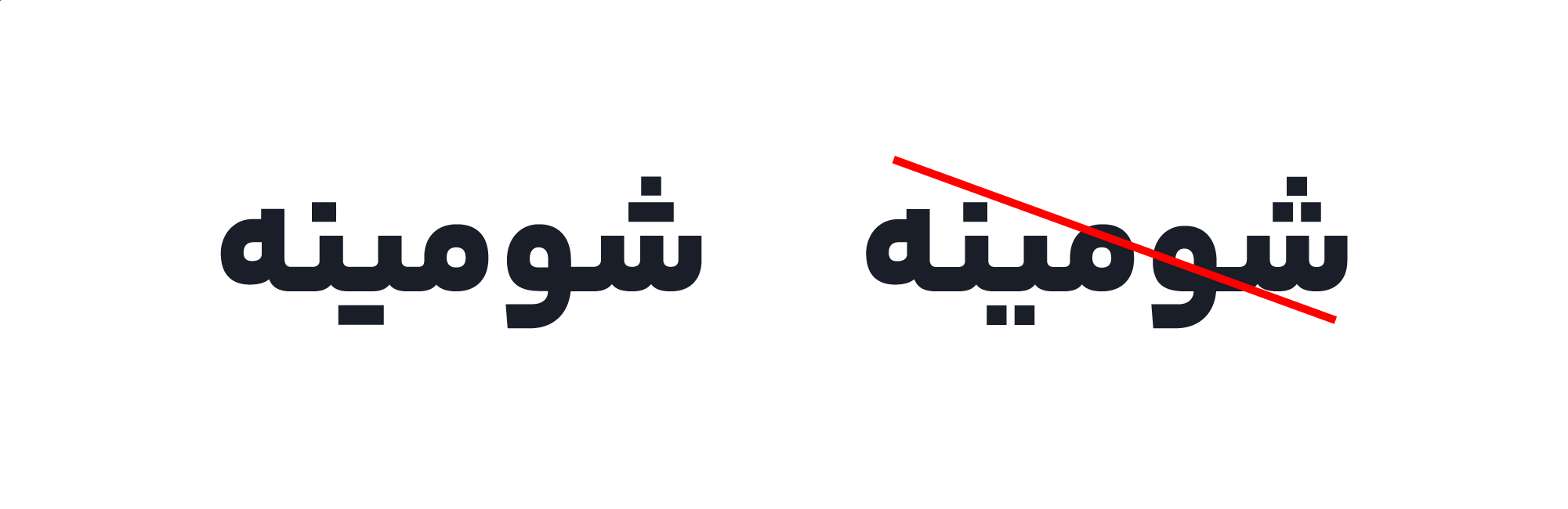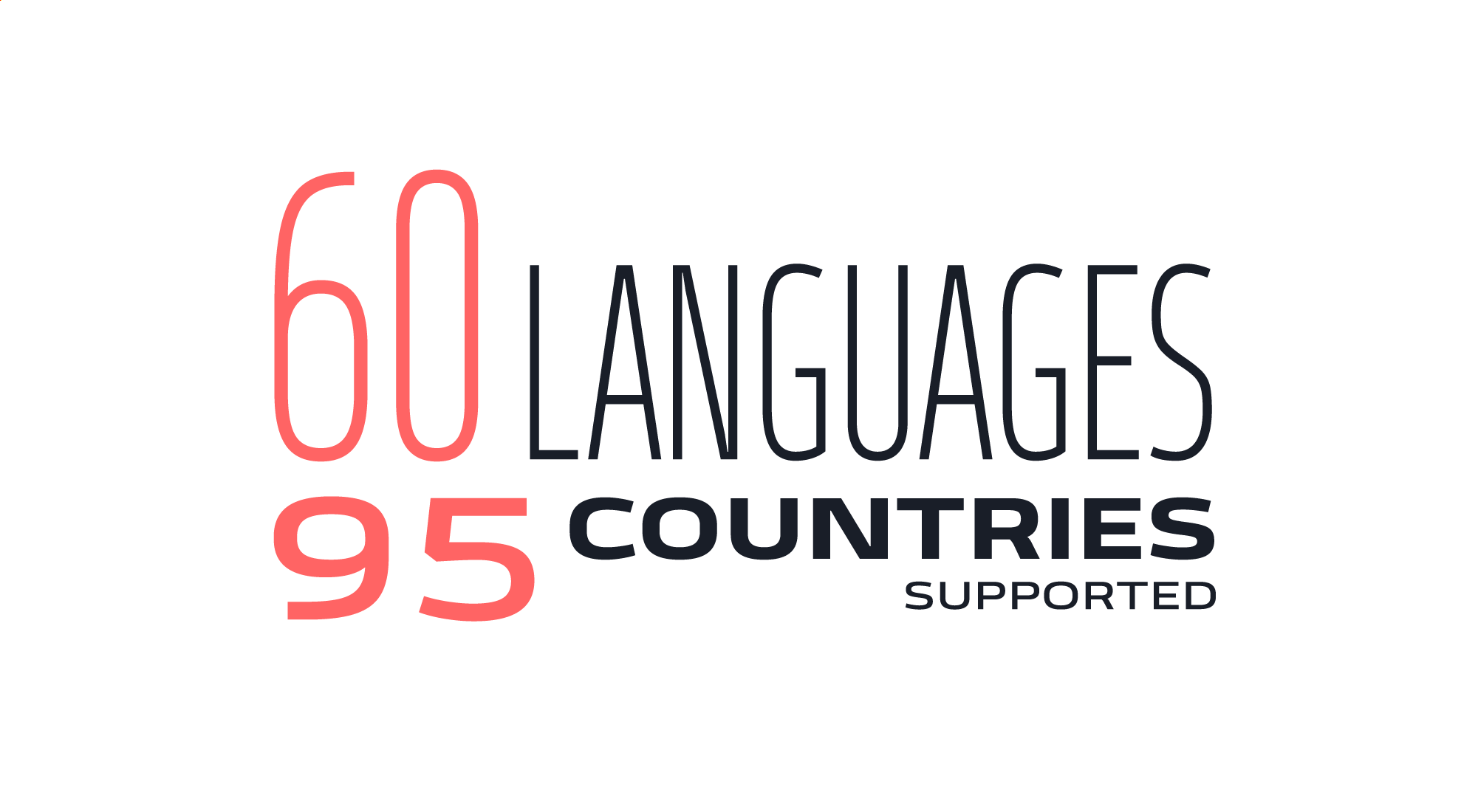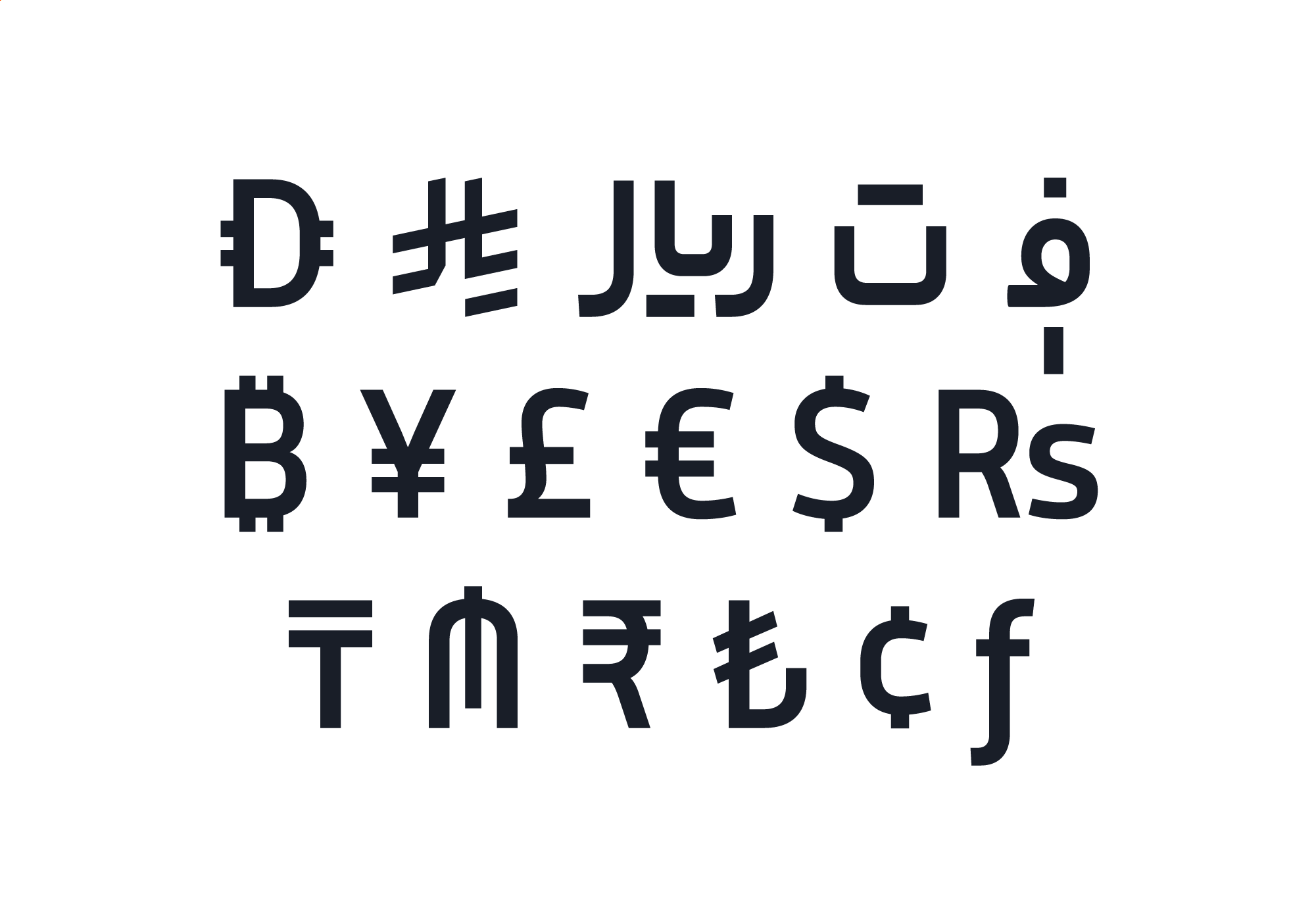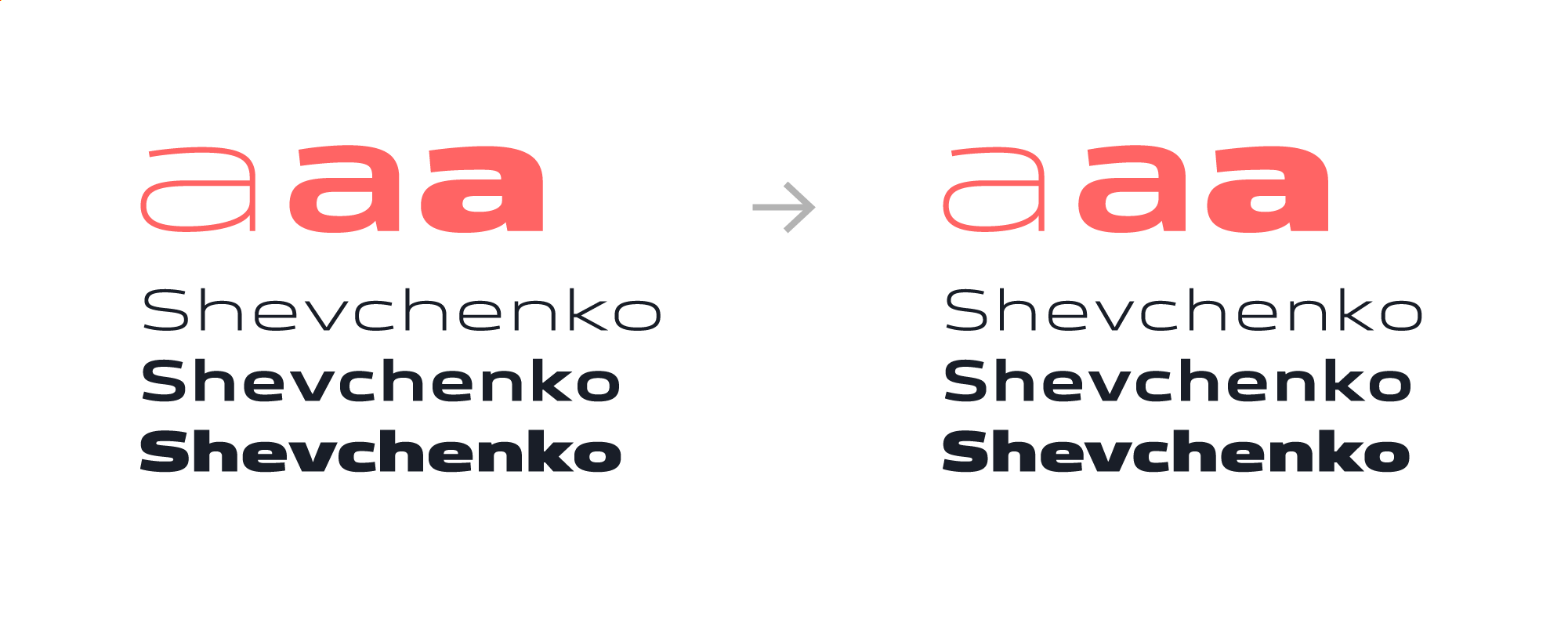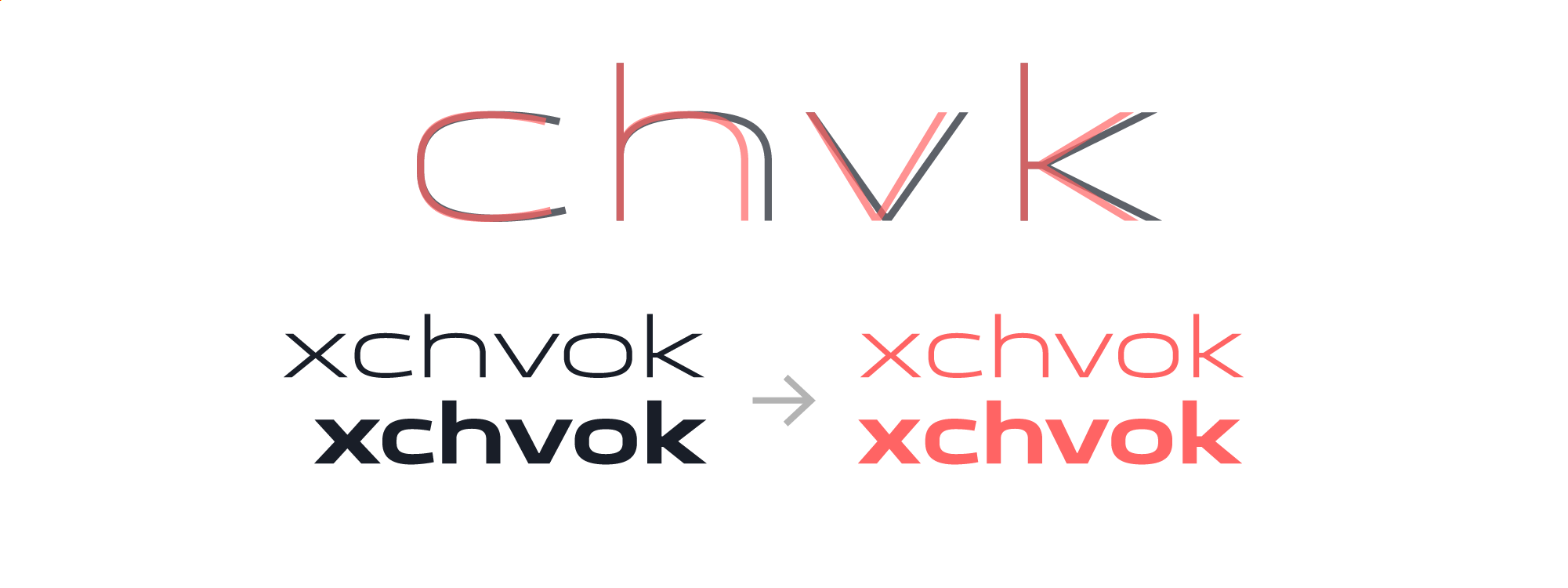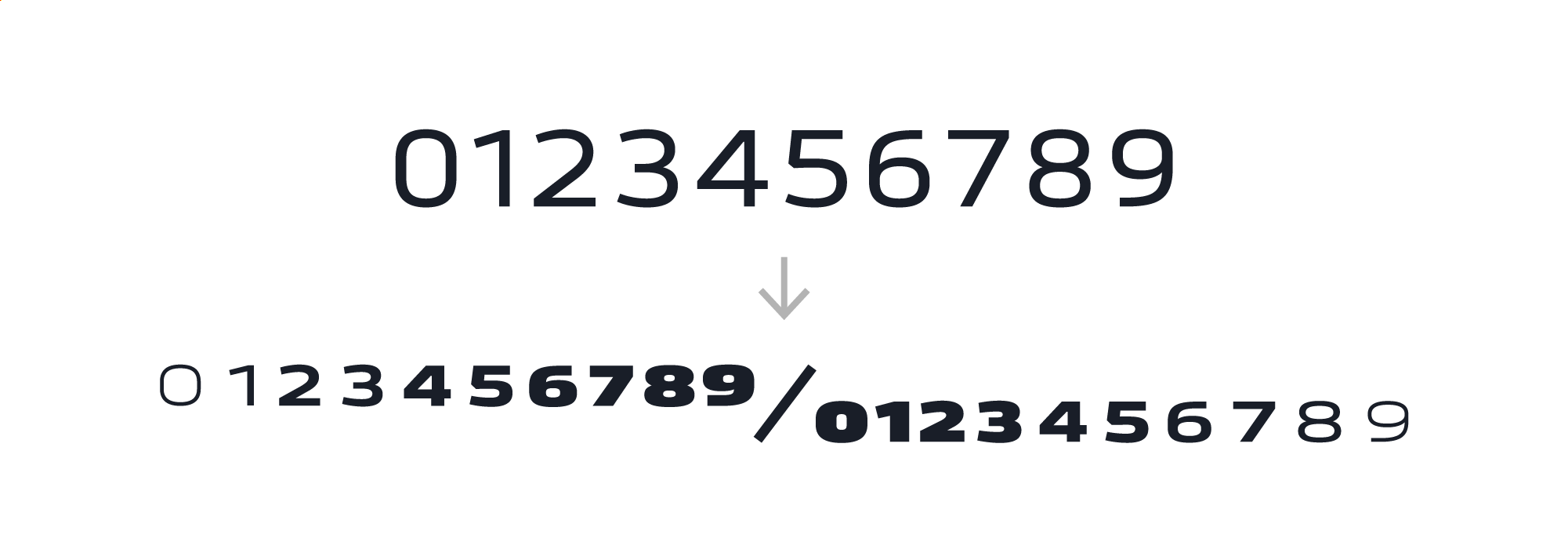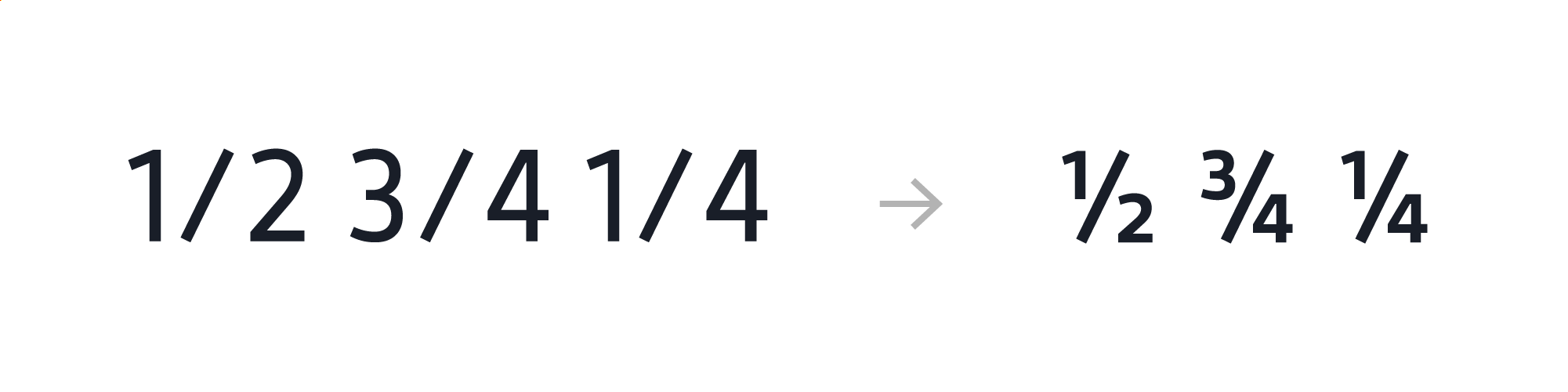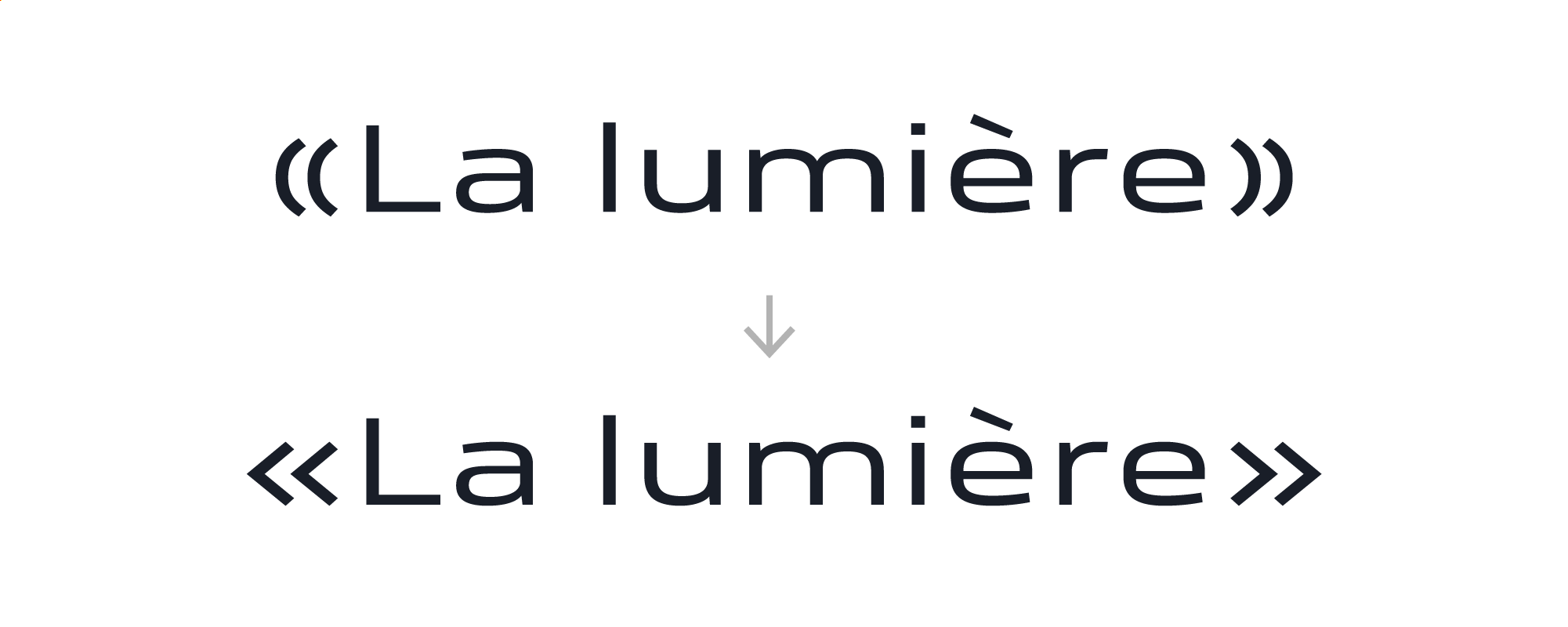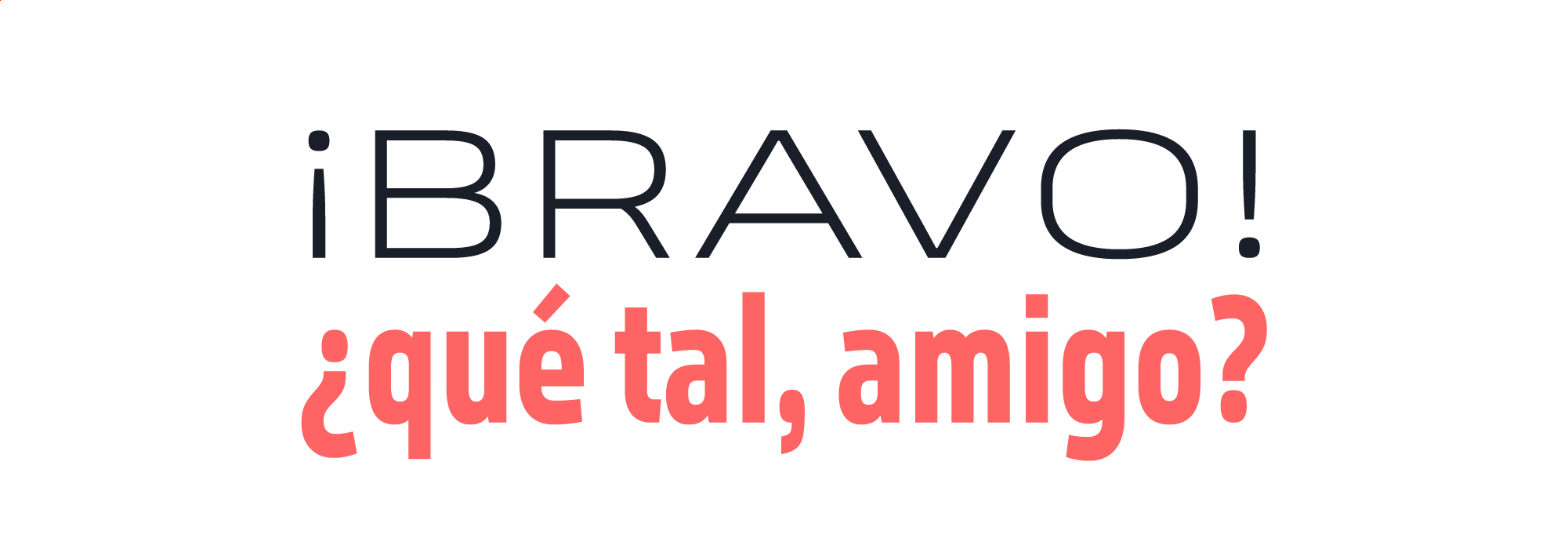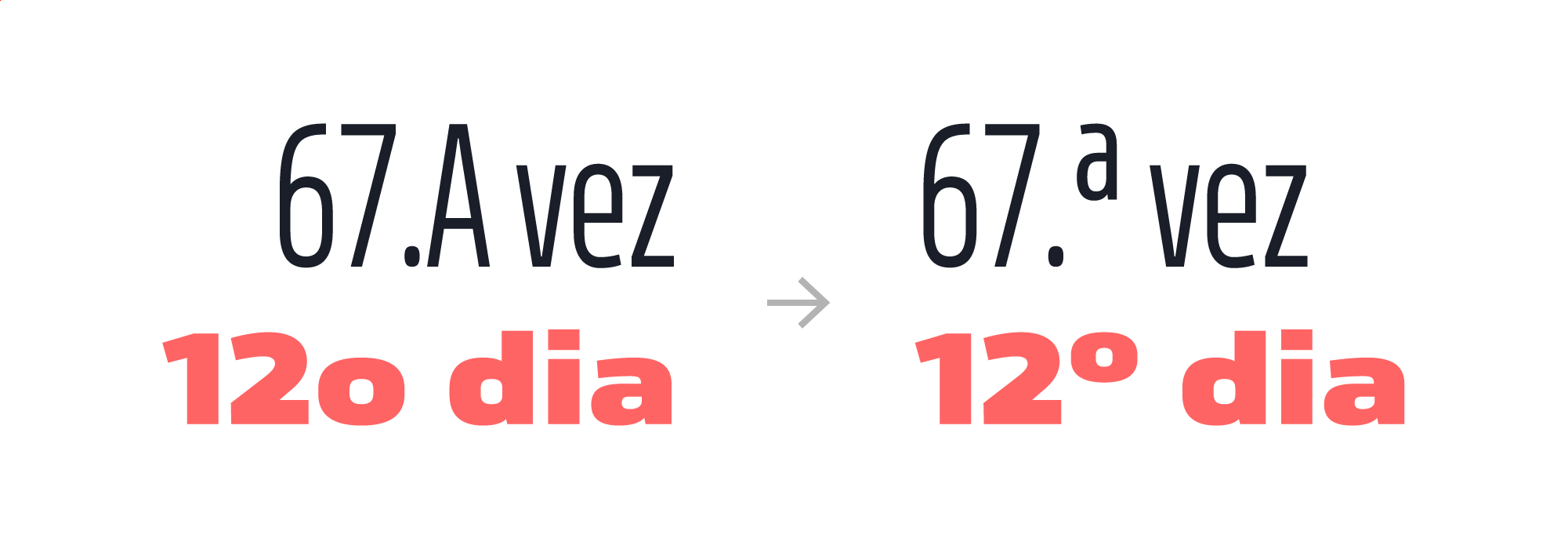
در نسخهی ۴ فونت یکانبخ چه تغییراتی میبینیم؟
۱. نسخهی نقطهجدا بهطور کلی از فونت حذف شد.
۲. کاراکترهای ۴۰ زبان با رسمالخط لاتین برای فونت طراحی شد. زبانهای اسپانیایی، فرانسوی، پرتغالی، آلمانی، ایتالیایی، ترکی، لهستانی، رومانیایی، هلندی، مجاری، چکی، سوئدی، فنلاندی، دانمارکی، نروژی، کرواتی، صربی، بوسنیایی، اسلواکی، اسلوونیایی، لیتوانیایی، لتونیایی، استونیایی، ایسلندی، ولزی، ایرلندی، گالیک اسکاتلندی، آلبانیایی، کاتالان، باسکی، گرینلندی، پرتغالی، گالیسیایی، برتونی، لوکزامبورگی، فریزی، آرومانیایی، مونتهنگرویی، آلمانی، فاروئی
۳. حالا فونت ۶۰ زبان را پوشش میدهد و در ۹۵ کشور قابل استفاده است.
۴. ده نماد واحد پولی جدید طراحی شد. حالا فونت جمعا ۱۷ واحد پولی را پوشش میدهد و در ۷۵ کشور قابل استفاده است: تومان، ریال، ریال عربستان، درهم، ؋، $، €، ¢، £، ¥، ₿، ƒ، ₺، ₹، ₨، ₼، ₸
۵. حروف لاتین سبک Expanded از نظر دیزاین و همآهنگی وزنها بازبینی و اصلاح شد.
۶. اعداد لاتین superscript و subscript طراحی شد. فیچرهای subs، sups و sinf برای استفاده از این اعداد است.
۷. کاراکترهای ¼، ¾، ½ طراحی شد. برای فعال کردن این امکان، فیچر frac را فعال کنید.
۸. کاراکترهای محلی زبانها طراحی و اضافه شد. مانند گیومهی فرانسوی و علامت سوال و تعجب اسپانیایی.
۹. حروف نشانگر ترتیبی a و n برای زبانهای لاتین ازجمله اسپانیایی و پرتغالی طراحی شد. فیچر ordn برای استفاده از این امکان است.
۱۰. کاراکتر Slashed Zero اضافه شد. برای جابهجا کردن این کاراکتر با صفر لاتین فیچر zero را فعال کنید.
۱۱. مشکل اعرابهای لله و الله برطرف شد. حالا فقط حرف آخر اعراب میگیرد.
۱۲. جای صفر فارسی تنظیم شد و کمی پایینتر آمد.
۱۳. ترکیبات لام-الف با کاراکترهای wavy hamza مربوط به زبان اردو و high hamza مربوط به زبان قزاقی و همچنین کاراکتر Kaf DotAbove مربوط به زبان پگون اضافه شد.
۱۴. ضخامت و جای Underline و Strikethrough تنظیم شد.